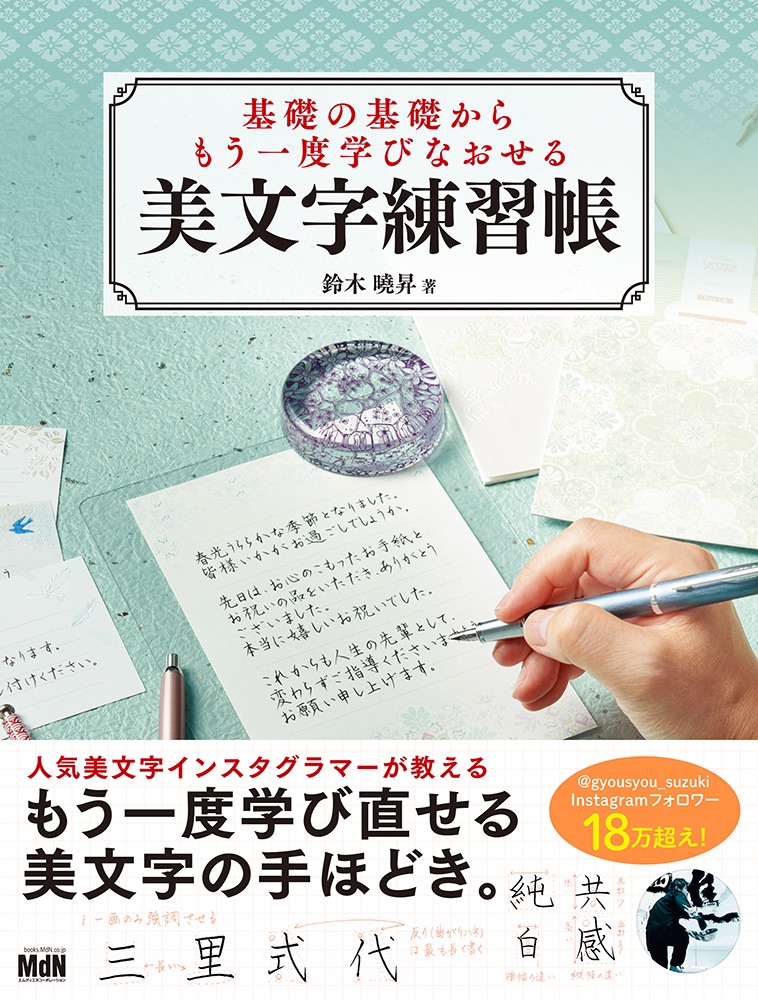
基礎の基礎からもう一度学びなおせる 美文字練習帳
インプレスグループでデザイン分野のメディア事業を手がけるエムディエヌコーポレーションは、テレビCMやNHK大河ドラマでの書道指導で注目を集め、インスタグラムをはじめSNSでも人気を博す書道家・鈴木曉昇氏が“基礎の基礎から”徹底的に手ほどきする、ペン字上達のための練習帳「基礎の基礎からもう一度学びなおせる 美文字練習帳」を発売した。
「基礎の基礎からもう一度学びなおせる 美文字練習帳」は、テレビCMやNHK大河ドラマでの書道指導で注目を集め、インスタグラムをはじめSNSでも人気を博す書道家・鈴木曉昇氏が、“基礎の基礎から”徹底的に手ほどきする、ペン字上達のための練習帳。
基礎習字、筆ペン字、ボールペン字の解説書を多数執筆する著者が、文章・文字を美しく見せるためのポイントを、伝統的書法に基づいた理論と独特の感性による文字表現で指導。ペン字初心者にはわかりやすく、中・上級者は基本に立ち返れるよう、基本線・点画、平仮名、カタカナ、漢字とステップを踏みながら、順を追ってしっかりと学ぶことができるよう構成されている。
著者の手書き文字による詳細な解説で“美文字”ポイントを理解したあとは、なぞり書きで文字の形を体感的に覚えていく。何度もなぞり練習ができるよう、手本となる例文と練習ページを多数掲載。この一冊を通して“美文字”を着実に習得することができる。
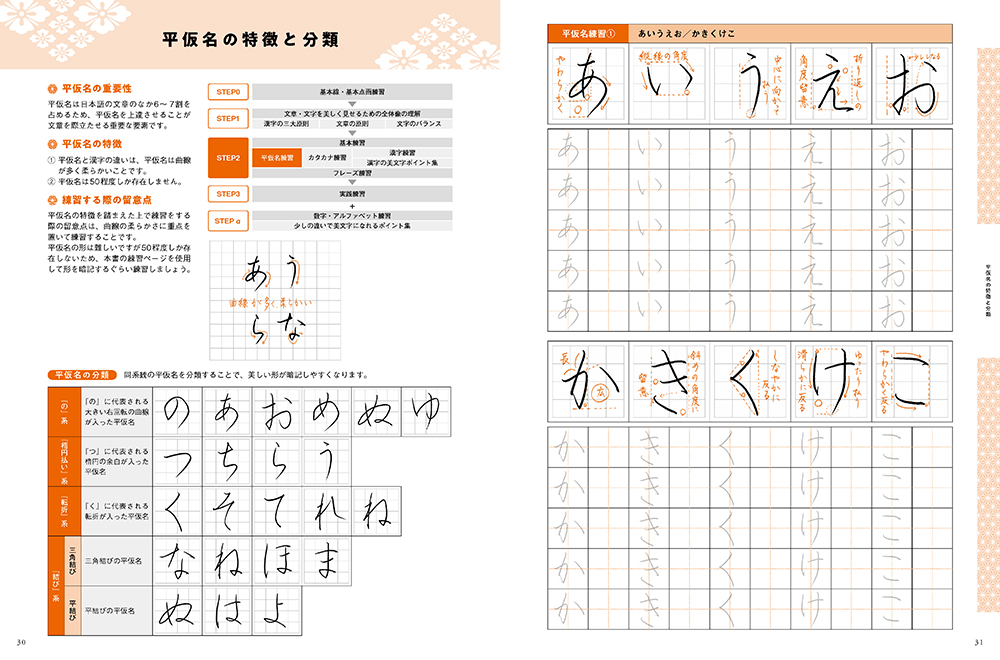
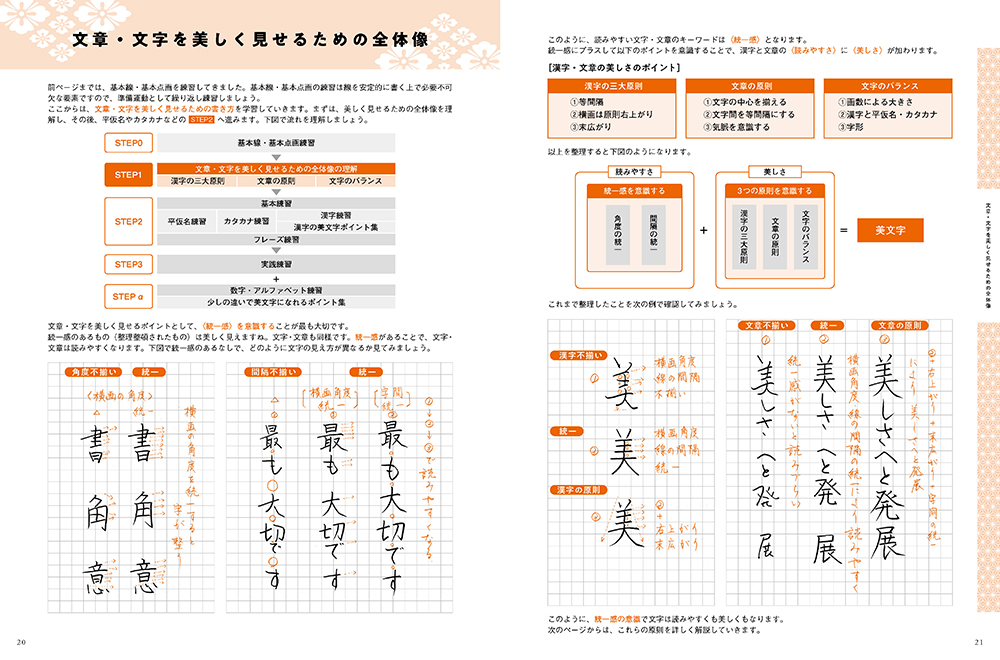
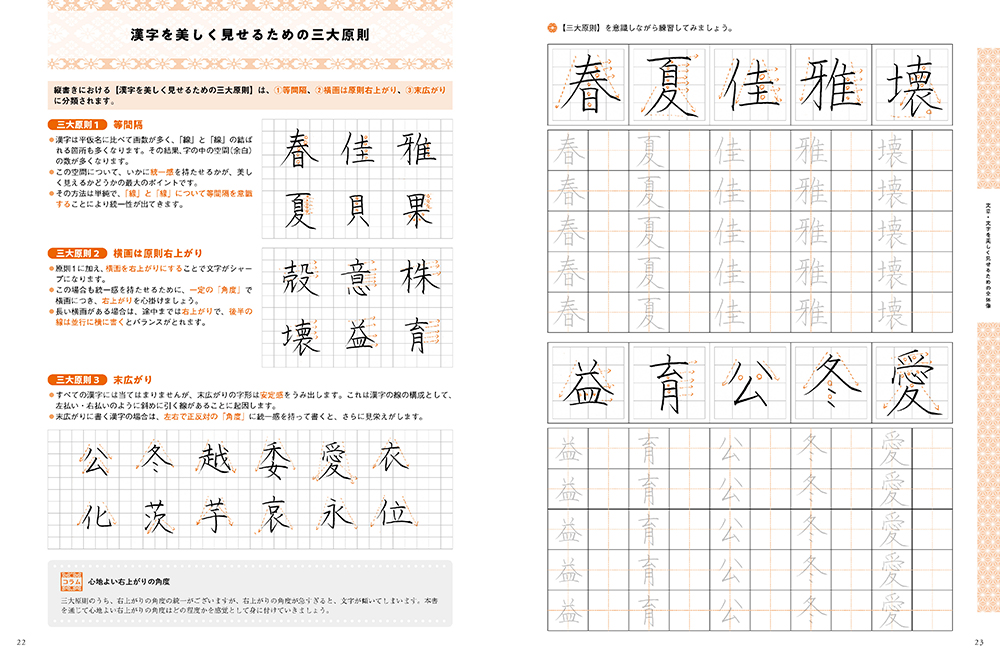
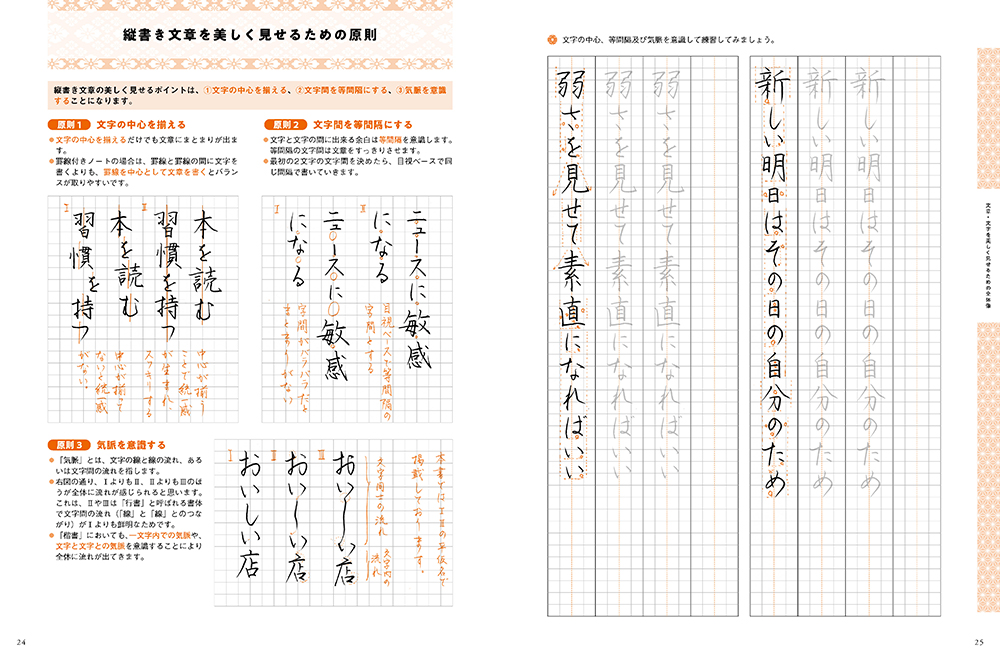
「基礎の基礎からもう一度学びなおせる 美文字練習帳」対象読者
・基礎から文字の書き方を学び直したい人
・美しい文字を書けるようになりたい人
・一般的なペン字練習では物足りない人
「基礎の基礎からもう一度学びなおせる 美文字練習帳」の特長
・5つのステップでわかりやすい構成
・著者の手書き文字による詳細な解説
・理論と実践を見開きで掲載
・ポイント解説が一目瞭然
・なぞり練習と練習マスを多数掲載
「基礎の基礎からもう一度学びなおせる 美文字練習帳」の内容
■ペンの種類&基本の持ち方
■基本線・基本点画を習得する
■文章・文字を美しく見せるための三大原則を学ぶ
■縦書き・横書きの文章の原則を学ぶ
■文字のバランスを意識する
■平仮名・カタカナの特徴を知る
■難しい平仮名を克服する
■漢字を美しく書くためのポイントを理解する
■漢字の組み立てのパターンを覚える
■漢字の字形を確認する
■日常でよく使うフレーズを練習する
■少しの違いで手慣れた雰囲気になる書き方を知る
■手本を見ながら実際に文章を書く
■添え書き、メモ書き、宛名書き、手紙文の例文